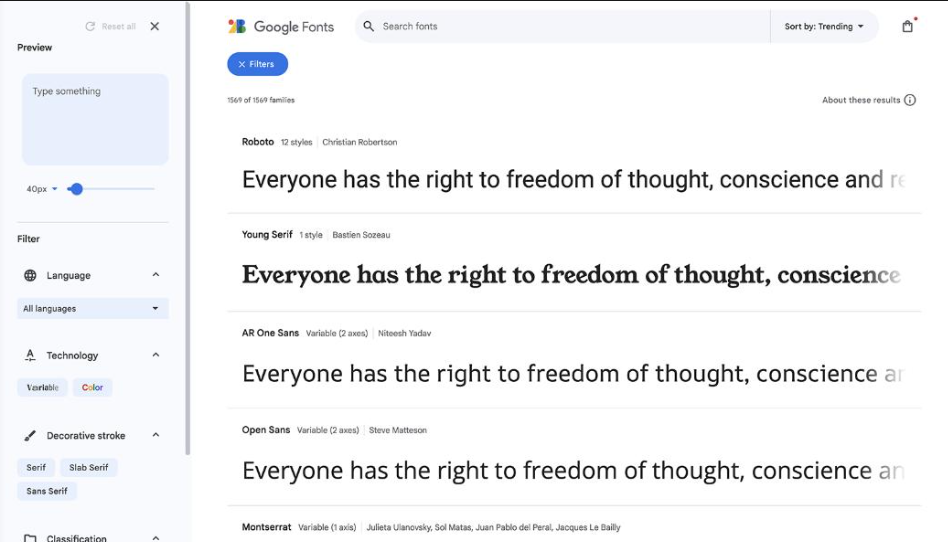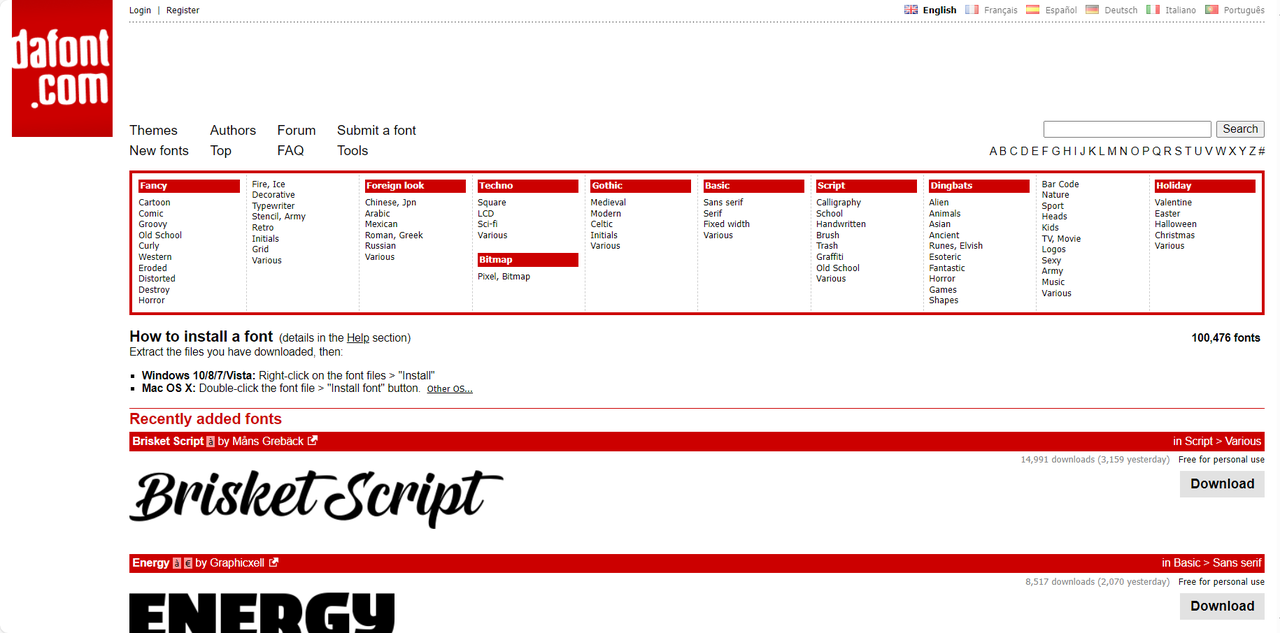
免费英语字体下载网站汇总,设计师必备无版权字体平台
一、字由
字由是一个集成字体资源、AI 字体、字体特效、字体应用于一身的知名字体管理工具,目前注册用户已超 2000 万,在设计师口中赞不绝口。字由的字体资源堪称丰富,拥有海量正版免费资源库,清晰且灵活的授权方式,满足用户的一切设计需求,其中免费商用字体有 3590+ 款,英文字体占比很大。最关键的是,通过字由客户端可实现在 PS、AI、ID、XD、Figma、Sketch、CDR 等设计软件中一键应用字体,无需下载,安装字体包,即可完成字体应用,省去了字体查找,下载,安装的麻烦。
除此之外,字由还提供 AI 识字服务,比如你在刷社交媒体时看到了某张图片上有一款你很喜欢的英文字体,但有不知道这款字体从哪找,只需要将图片上传到字由的 AI 识字功能页,它会自动识别图片内字体名称,并给你推荐几款相似字体。每款字体都会标注它的授权方式哦,所以你完全可以放心下载使用,不会有任何版权问题出现。
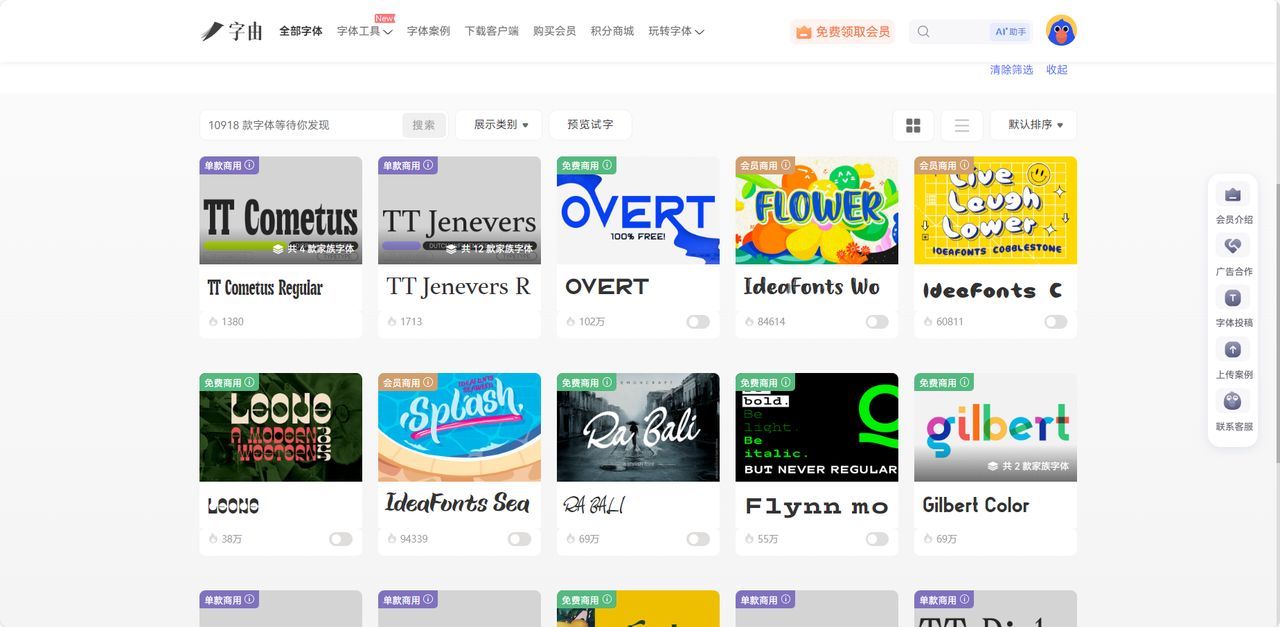
二、Google Fonts
Google Fonts 是面向全球设计师开放的开源字体资源站,提供上千款高品质英语字体,包含衬线体、无衬线体、手写体、涂鸦体、创意体等等。为了便于用户快速搜索想要的字体,它更是为大家提供了系统化的筛选工具栏,可以按照风格、笔画粗细、字形宽度、字符倾斜角度等方面来进行精细化检索,如果你提前预设好了想要什么类型什么大小的英语字体,在这里你能快速定位字体。对于很多网页设计师而言,这个网站使用起来会更加顺手,不需要手动下载字体文件,直接在 Google Fonts 的字体库中选中心仪字体,紫铜会自动生成标准的代码,用户直接复制粘贴到对应的网页当中即可。另外,所有入驻 Google Fonts 的字体均开源免费商用,用户完全不需要担心任何授权费用。
三、DaFont
如你需要一个视觉张力强且瞬间抓住别人目光的英文字体,那么 DaFont 绝对是你值得收藏起来的网站!它拥有数量最庞大的英文字体,相较于其他的网站,DaFont 更像是一个充满想象力、新鲜感以及创意设计的宝库。我非常喜欢该网站的字体分类栏,从恐怖色彩拉满的哥特式风格到涂鸦气息扑面而来的喷漆风格,再到中世纪时代的复古风格,又或者是多彩泡泡样式的手写风格,几乎每一款字体都有他独特的魅力,都是你之前没见过的样子。在下载英语字体这方面,DaFont 支持免注册一键下载字体压缩包,压缩包内一般还会附带一个文本文档,里面清晰记载了字体的使用指南以及这款字体的授权说明,所以大家千万不要把它当成没用的东西删掉,一定要仔细查看哦。
四、Font Squirrel
大家对于 Font Squirrel 肯定也不陌生了,它专门为用户提供免费可商用的英语字体。Font Squirrel 从来都不以字体资源的数量取胜,而是以极高的审核门槛把关字体,网站内的字体都是经过逐一排查后选择的既有艺术性美观性,又能支持商业用途的。大家选择字体的时候可以注意一下每款字体下方的图标,代表的是该字体能否被应用于电脑、手机、平板、网页,图标点亮就表明可以使用。Font Squirrel 支持多种格式的下载,比如 WOFF、WOFF2、EOT、TTF、SVG 等,这对于设计师来说非常方便,不管后续将英语字体用于哪个软件都能一键导入。
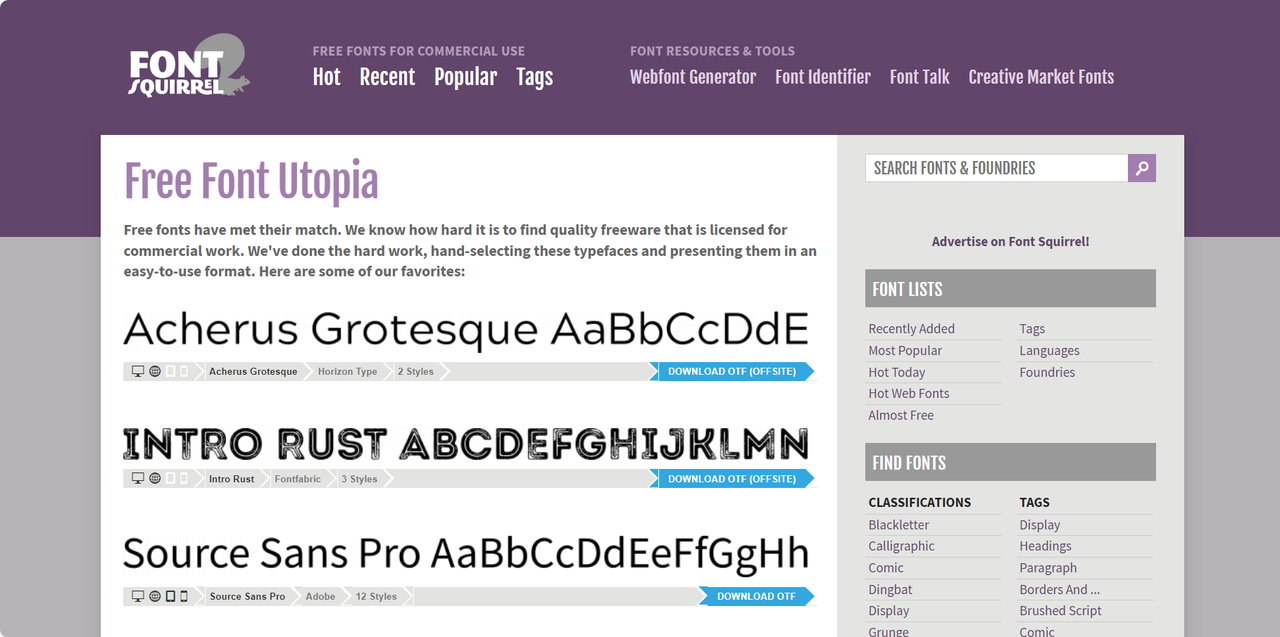
五、FontSpace
与其说 FontSpace 是免费英语字体下载网站,不如说这是一个由全球字体创作者、设计师用户、排版艺术家、美学爱好者共同搭建出来的超高活跃度字体交流社区。在这个网站内,每一位用户都可以上传自己的作品,其他用户也可以点赞、收藏、评论自己喜欢的字体,说不定还可以和相关的设计师交朋友呢。目前为止 FontSpace 已经累积了 11 万款字体资源,当你选择完英语字体之后,可以在线修改预览框内的文字,甚至还能设置粗体、斜体或下划线等效果,或者切换背景色来帮助你更直观地评价字体是否适合自己。我觉得 FontSpace 最大的亮点就是稳定更新的新字体推送政策,因为这个网站用户的活跃度非常高,所以特色推荐页面几个每个月都会向用户推送 15-20 套全新的可商用英文字体模板,这也是很多设计师们的一个潮流趋势获取基地。